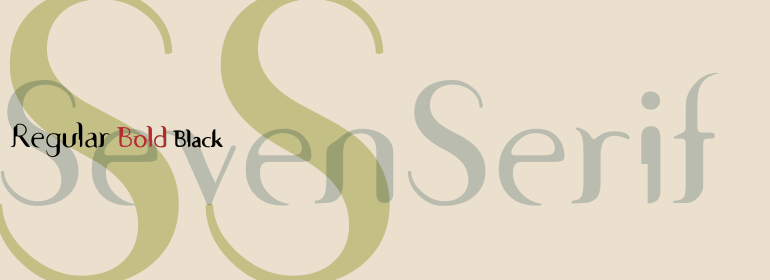
Seven™Serif
Seven™Serif,这款字体结构工整、笔画清晰,兼顾美观与易读性,适用于标题、正文、海报、包装、LOGO 等多种场景。字形优雅稳定,风格百搭耐看,适配日常排版与创意设计,让文字呈现更舒适、更具质感。Seven™Serif一笔一画,皆是细节,以均衡的比例、流畅的线条打造舒适视觉体验,字形端正大气,风格简约现代。无论是商业设计、品牌宣传还是日常排版,都能轻松驾驭,让文字更有格调与力量。Seven™Serif字体下载。